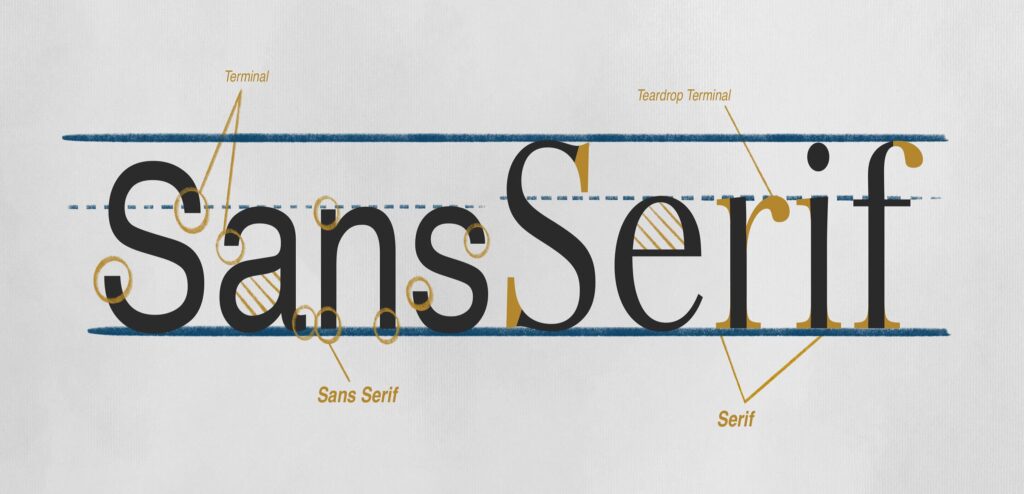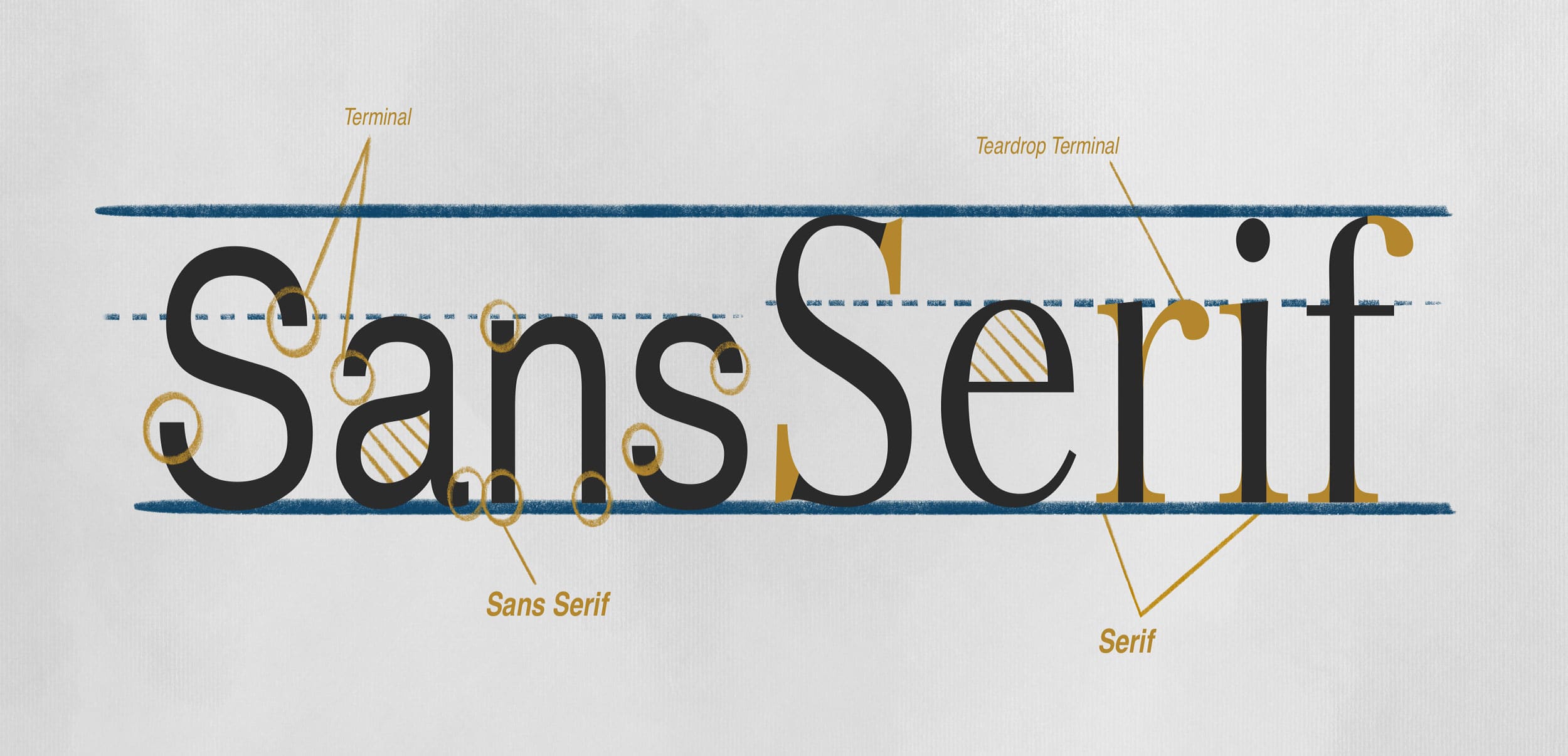
Sans-serif là nhóm font được dùng nhiều nhất trong thiết kế hiện đại, nhưng không phải font nào cũng hỗ trợ đầy đủ tiếng Việt. Ở bài viết này, In Viva tổng hợp các font đã được việt hóa đẹp và ấn tượng kèm link tải font Sans-Serif trực tiếp cũng như gợi ý cách sử dụng phù hợp từng mục đích thiết kế, in ấn.
Sans-serif là gì? Vì sao font này được dùng trong thiết kế và in ấn?
Font sans-serif là font chữ không có chân – không có nét vuốt nhỏ ở đầu và cuối mỗi nét chữ như nhóm serif. “Sans” trong tiếng Pháp có nghĩa là “không có”, nên sans-serif đúng nghĩa là “không có chân”. Một số lý do mà nhóm font này được sử dụng trong thiết kế kỹ thuật số và in ấn hiện đại:
- Dễ đọc trên màn hình: ở kích thước nhỏ và độ phân giải thấp, font sans-serif hiển thị sắc nét hơn serif vì không có các nét chân nhỏ dễ bị vỡ pixel.
- Cảm giác hiện đại, trung tính: sans-serif không gắn với phong cách thời kỳ nào như serif, phù hợp với giao diện app, website, bao bì sản phẩm và tài liệu doanh nghiệp đương đại.
- Linh hoạt trong phối font: hầu hết bộ font sans-serif đều có nhiều weight từ Thin đến Black, đủ để dùng cho cả tiêu đề lẫn nội dung trong một thiết kế mà không cần thêm font thứ hai.
Top 5+ font sans-serif Việt hóa đẹp
Danh sách dưới đây tập trung vào những font sans-serif có hỗ trợ đầy đủ tiếng Việt, tải miễn phí và dùng được cho cả web lẫn in ấn.
| Font | Đặc điểm nổi bật | Phù hợp cho | Nguồn tải |
|---|---|---|---|
| Be Vietnam Pro | Thiết kế riêng cho tiếng Việt, 18 weight, dấu chuẩn không chồng | Bao bì, tài liệu doanh nghiệp, web Việt | Google Fonts |
| Roboto | Font mặc định Android, trung tính, hỗ trợ Unicode tiếng Việt | App, tài liệu kỹ thuật, báo cáo | Google Fonts |
| Nunito | Tròn góc, thân thiện, hỗ trợ tiếng Việt đầy đủ | Giáo dục, app trẻ em, thương hiệu lifestyle | Google Fonts |
| Inter | Tối ưu màn hình độ phân giải cao, metric chuẩn hóa chặt chẽ | UI/UX, sản phẩm công nghệ | Google Fonts / rsms.me/inter |
| MS Sans Serif | Font hệ thống Windows cổ điển, không phóng to tốt | Mở file tài liệu cũ, phần mềm legacy | Có sẵn trên Windows |
Mỗi font trong danh sách trên có nguồn tải khác nhau. Xưởng In Viva tổng hợp danh sách font sans-serif
Cách chọn font sans-serif phù hợp với từng mục đích thiết kế
Không phải font sans-serif nào cũng phù hợp với mọi dự án. Bốn tiêu chí dưới đây giúp thu hẹp lựa chọn nhanh hơn thay vì thử từng font một.
| Tiêu chí | Khuyến khích |
|---|---|
| In ấn hay digital | In ấn: Be Vietnam Pro, Roboto (nét rõ ở cỡ nhỏ). Digital, màn hình retina: Inter, Be Vietnam Pro |
| Tiêu đề hay nội dung chính | Tiêu đề: font có weight đậm, dáng đặc trưng. Nội dung dài: Roboto Regular hoặc Inter Regular ở 14–16px |
| Thương hiệu trẻ hay chuyên nghiệp | Trẻ, thân thiện: Nunito, Be Vietnam Pro. Doanh nghiệp, B2B, fintech: Inter, Roboto |
| Hỗ trợ nhiều ngôn ngữ | Tài liệu song ngữ Anh – Việt: Be Vietnam Pro hoặc Inter (cả hai hỗ trợ Latin Extended đầy đủ) |
Font sans-serif và serif khác nhau như thế nào?
Serif có nét chân nhỏ ở đầu và cuối mỗi nét chữ, tạo cảm giác cổ điển, trang trọng. Sans-serif không có chân, trông hiện đại và sạch sẽ hơn. Sans-serif phù hợp màn hình; serif phù hợp văn bản in dài.
Font sans-serif nào tốt nhất cho thiết kế bao bì sản phẩm Việt Nam?
Be Vietnam Pro là lựa chọn hàng đầu vì thiết kế riêng cho tiếng Việt, dấu chuẩn, không bị chồng chéo khi in nhỏ. Roboto là lựa chọn thứ hai nếu cần font trung tính, quen thuộc với đại đa số người dùng.
MS Sans Serif và Arial khác nhau ở điểm nào?
MS Sans Serif là font bitmap cũ của Windows, chỉ trông tốt ở một số kích thước cố định. Arial là font vector, phóng to thu nhỏ tùy ý vẫn sắc nét. Với thiết kế hiện đại, Arial hoặc các font Google Fonts thay thế tốt hơn MS Sans Serif.